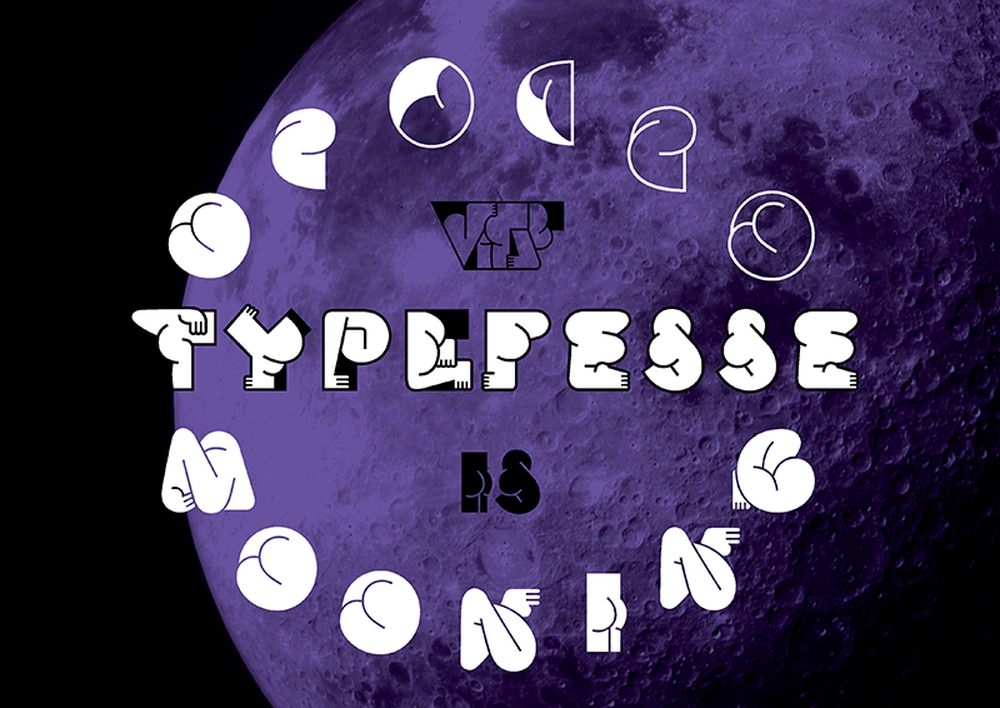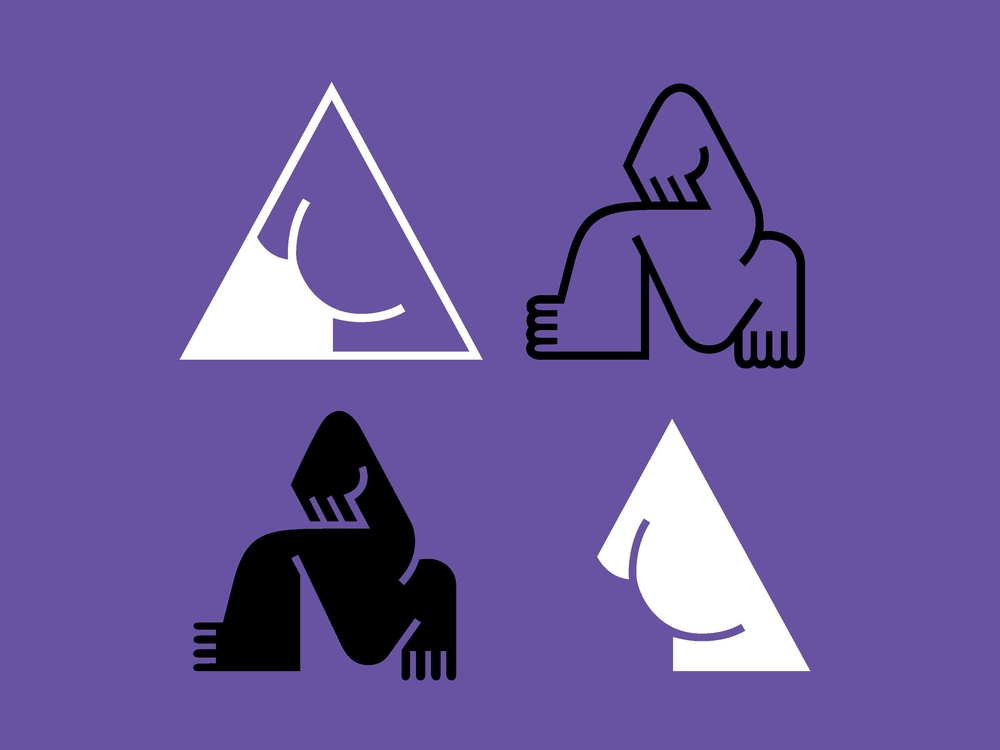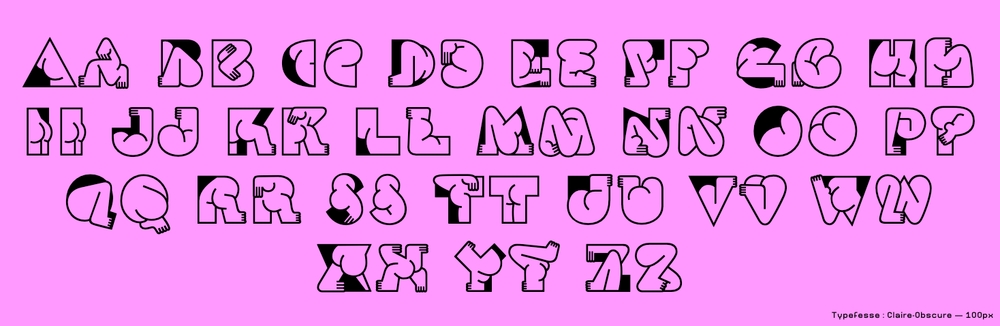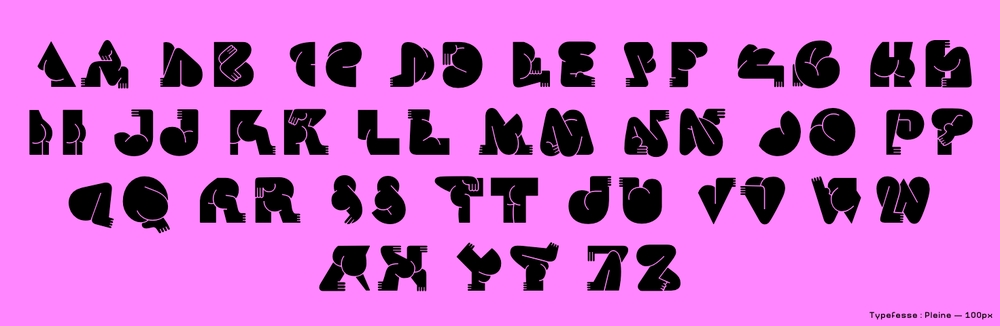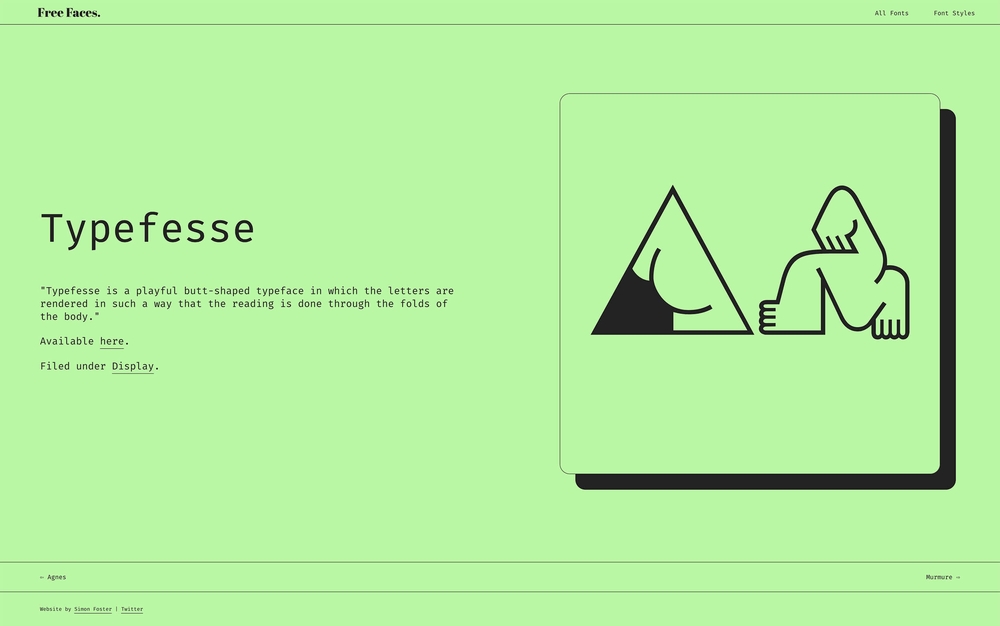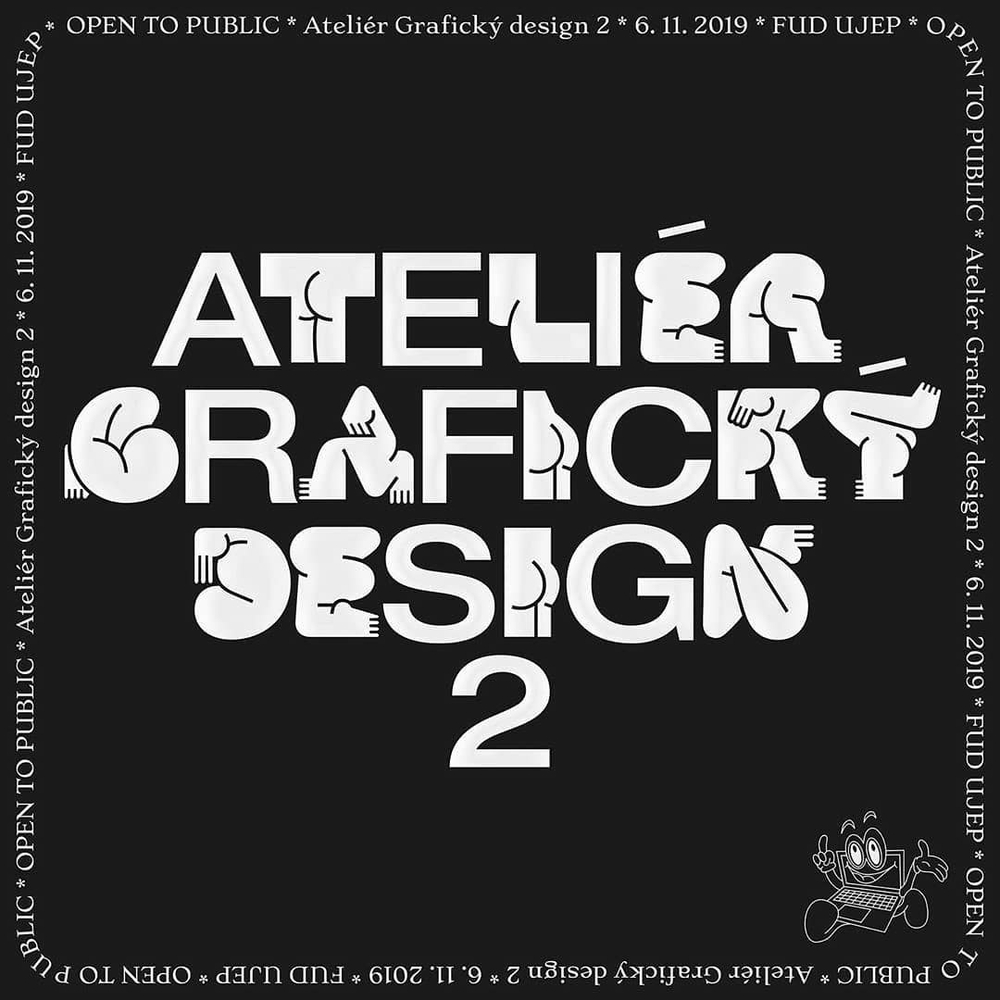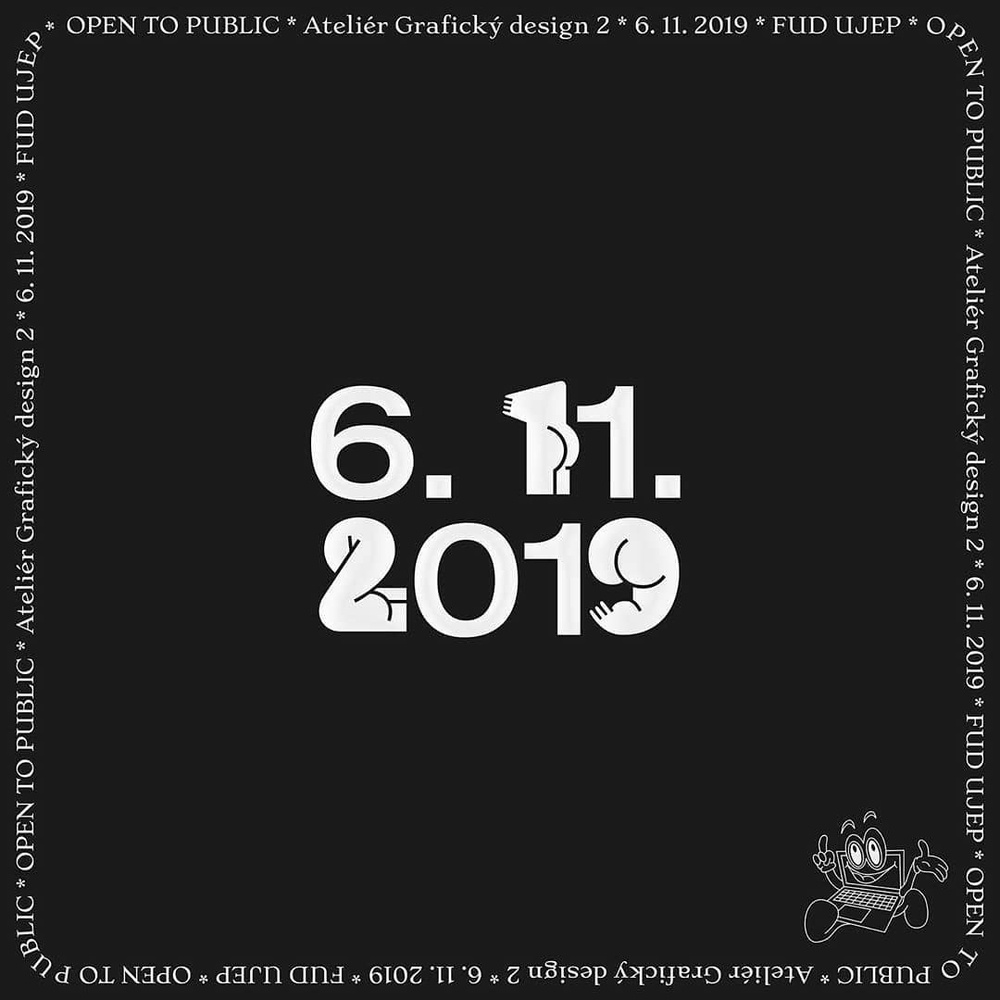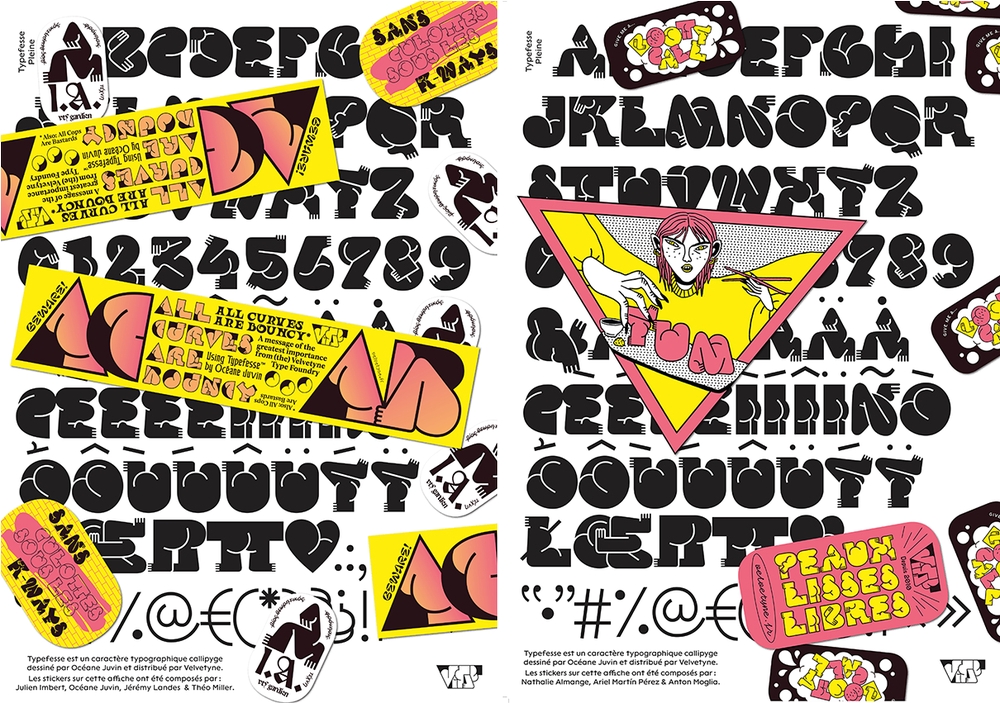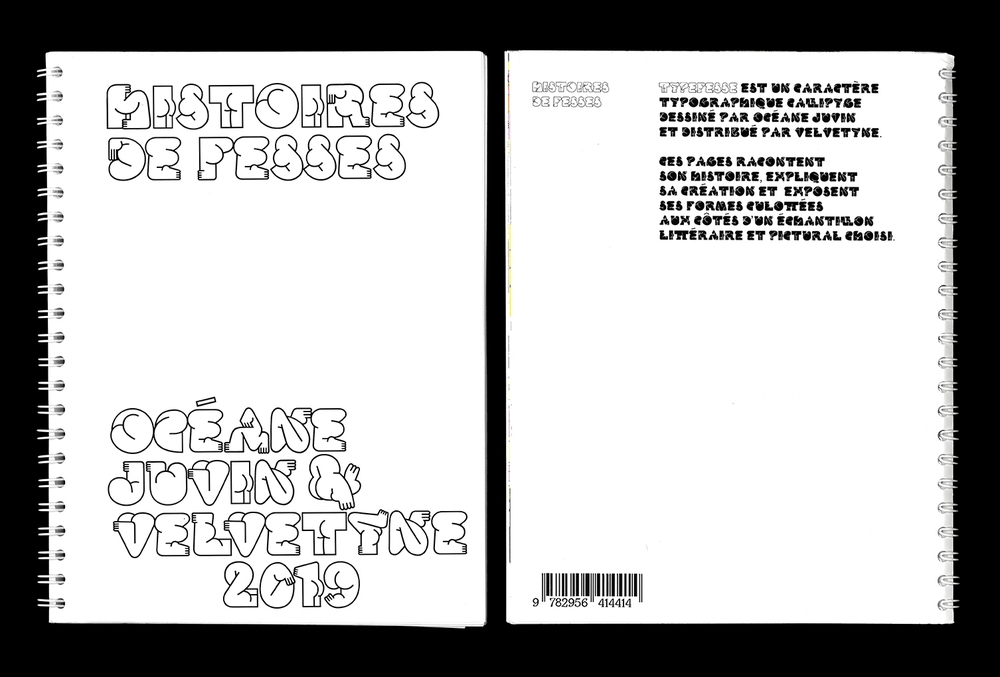
Typefesse
Typefesse 被列入 Typographica 的 2019 年最受欢迎的字体。Typefesse 是一种俏皮的屁股形状的字体,其字母的呈现方式是通过身体的褶皱进行展示的。这款字体的设计师是一名来自法国的平面设计师 Océane Juvin ,毕业于巴黎埃斯蒂安的字体设计专业。设计师对于字体的灵感来自于两种相同又不同群体的结合——身体与字母,它们交替地隐藏或暴露自己,可以说不知是身体变了形,还是字母出了轨。
Typefesse是一种在阅读、观察和窥探之间产生混淆的字体,是一种标题字体,尽管它在小尺寸的正文中具有令人惊讶的可读性。这些裸露的字母形态方佛在与世俗的眼光作斗争,以其旺盛的生命力扰乱其可读性。所以它的三种风格被命名为月亮和它的奥秘。
Typefesse是一款有趣俏皮的“翘臀”免费可商用英文字体,包含两种字体形态,大小写都有各自不同的变化。
Claire-Obscure,是最灵活敏捷、扭曲的一款字重,像似身体被迫蜷缩起来适应字母内部。同时,也是最像插画风格的图形,字母被演示为各种各样的锁孔,像游戏空间。当它们组合在一起变成一个词时,它们又似乎相互依偎,使字母关系看起来更加亲密。
Pleine,这种字重就像敲定了画面的中心位置,即使最小尺寸的字体都具有最大的可读性,可以算作为 Claire 和 Obscure 风格之上的一个附加层。
这款字体可以运用在各种有趣的平面设计场景上,就算使用在普通的画面,整个风格也会变得非常有趣起来。